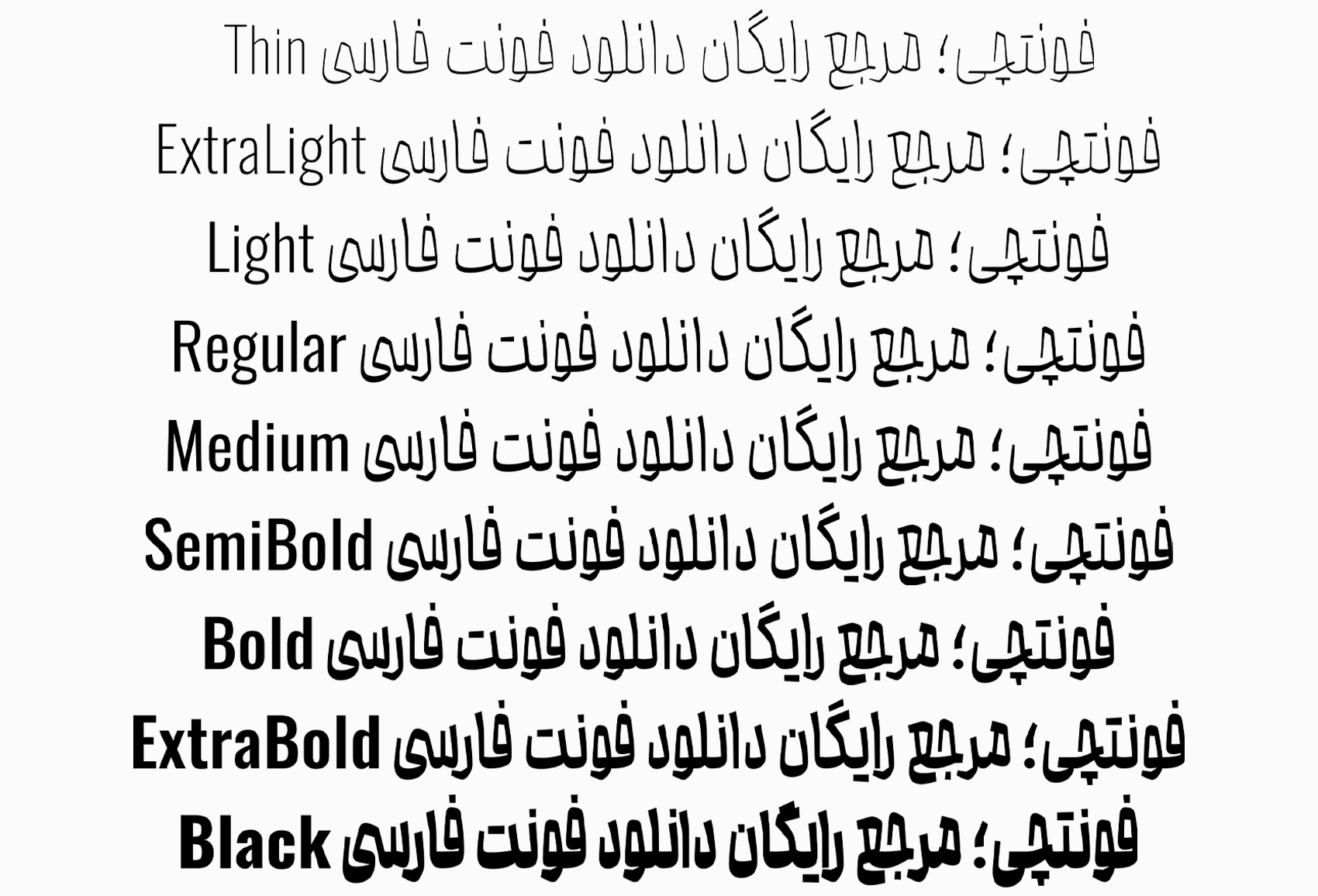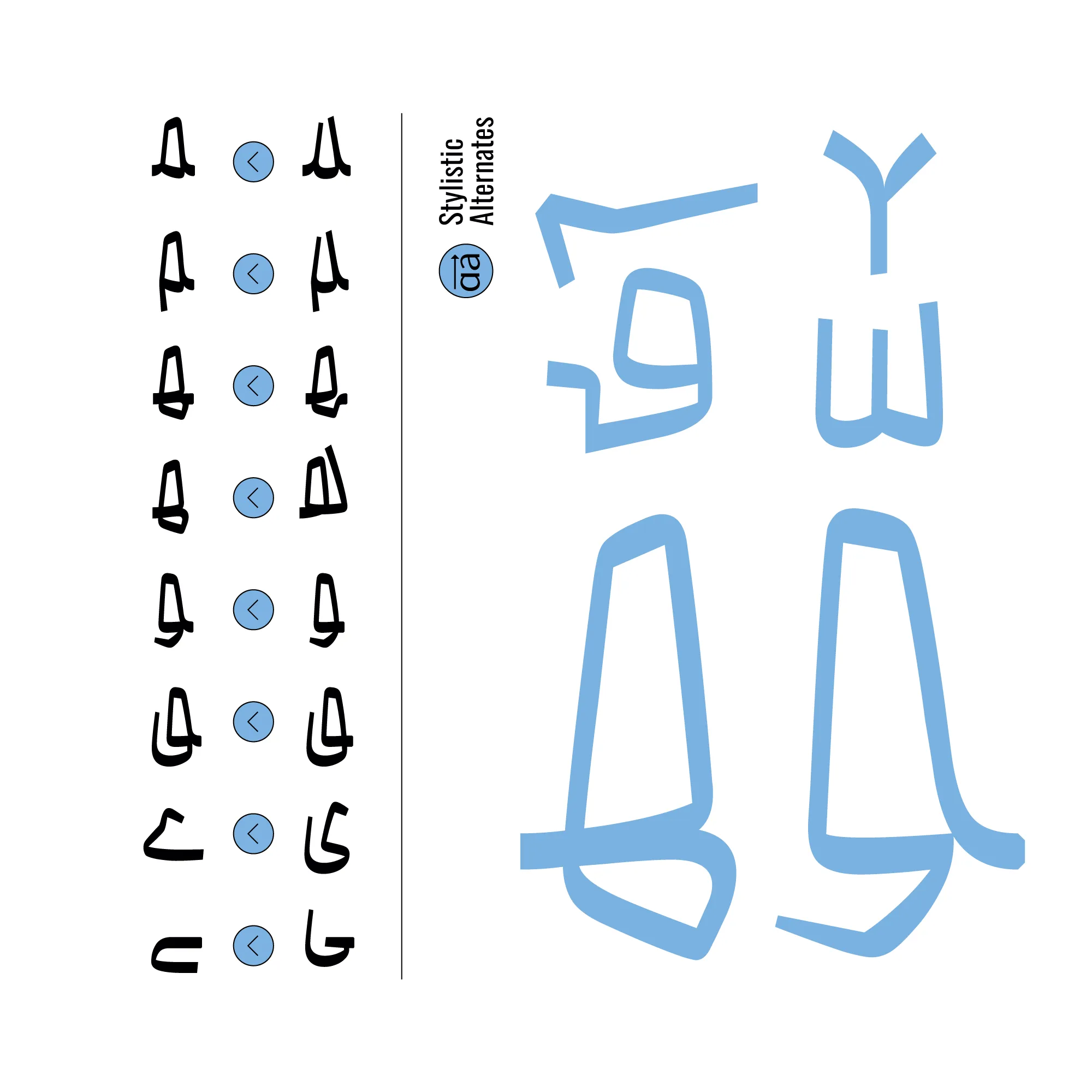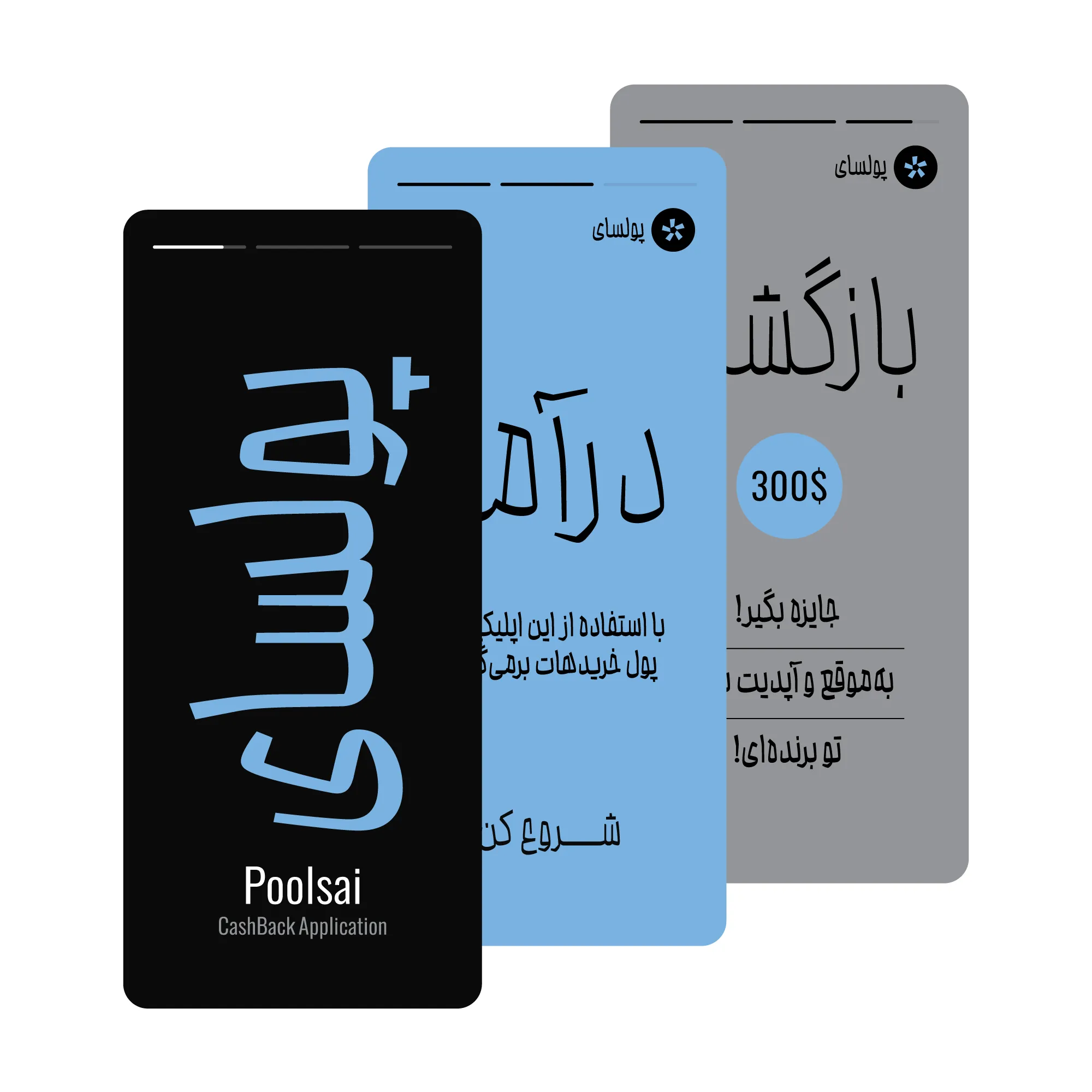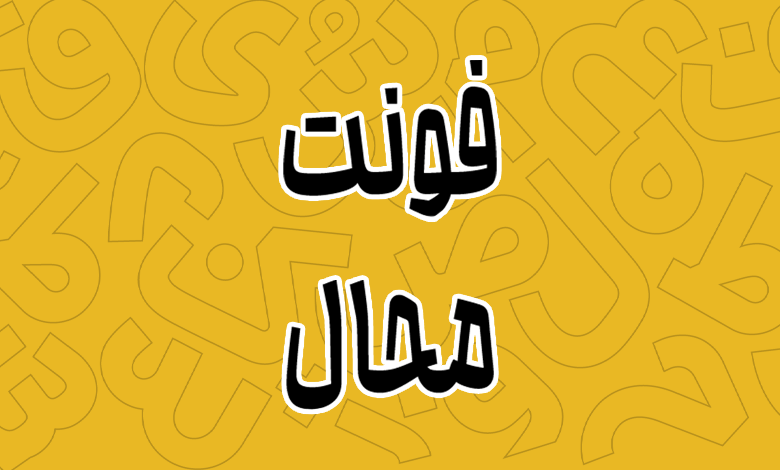
فونت محال (Mahal)
فونت محال (به انگلیسی: Mahal) قلمی با طراحی کاملا هندسی و ظاهری شبیه به خط نسخ است. این خط فارسی دارای ارتفاعی کشیده است و حروف از راستای افقی دارای ظاهری فشرده هستند که همین ویژگیها آن را به قلمی مدرن برای تبلیغات تبدیل کرده است. فونت محال رایگان نبوده و با توجه به پشتیبانی که از ۵ وزن مختلف و ویژگیهایی همچون نسخه مخصوص اعداد فارسی، حروف جایگزین و گلیفهای تزئینی و ریال را در خود دارد، در قالب ۳ بسته قابل دانلود است.
سید ناصر خادم که پیش از این قلمهایی مثل فونت ادامه و فونت مدام را طراحی کرده، این فونت جدید را بهمنظور قلمی برای تبلیغات، خصوصا در فضای دیجیتال و شبکههای اجتماعی معرفی کرده است. قلمی که با ظاهر پرانرژی و مدرن خود، دارای شخصیتی آرام و درونگرا است.
در ادامه این نوشته از سایت دانلود فونت فونتچی، به نقد و بررسی کامل فونت محال خواهیم پرداخت. خطی فارسی که میتوانید از آن بهترین استفاده را برای فضای تبلیغاتی و استفاده در عناوین به کار ببرید. فونتی که دارای ظاهری نمایشی ولی روحیهای نوجوان است.
فونت محال بهعنوان یک تایپفیس خلاقانه و نمایشی، با روحیهای معترض و جسورانه طراحی شده است. این فونت توانایی انتقال پیامهایی قوی و تاثیرگذار را دارد و مناسب افرادی است که به دنبال ایجاد تمایز و جلب توجه در طراحیهای خود هستند. در عین حال، فونت Mahal با حفظ انرژی و شور ذاتی خود، گاهی آرامش و عمق درونگرایی را نیز منتقل میکند.
سبک طراحی و وزن فونت محال
فونت فارسی محال با جزییات دقیق و فرمهای بازیگوشانه حروف، انتخابی ایدهآل برای تیترها، شعارها و متنهای کوتاه است. این ویژگیها آن را به گزینهای مناسب برای کاربردهای تبلیغاتی، طراحی تصاویر و تامنیل در شبکههای اجتماعی، استارتاپها، طراحان بازی، و پروژههای وب و اپلیکیشن تبدیل کرده است.
محال از ۹ وزن متنوع پشتیبانی میکند که از وزن بسیار نازک تا بسیار تیره را شامل میشود. در وزنهای سبک، ضخامت حروف شباهتی به تایپفیسهای مونولاین پیدا میکند، در حالی که در وزنهای سنگینتر، کنتراست بیشتری در ضخامت حروف دیده میشود که به طراحی عمق و جذابیت بصری بیشتری بخشیده و همچنین ظاهری نمایشیتر بهخود میگیرد.
یکی از مهمترین چالشهای طراحی فونت محال، ترکیب عمودی بودن فرم حروف با حفظ خوانایی و اصول رسمالخط فارسی بوده است. کنترل فضای بین حروف، هماهنگی خطوط عمودی، و تنظیم ارتفاع دندانهها و حلقههای باز و بسته، از جمله جزئیات پیچیدهای بودند که در این پروژه بهخوبی مدیریت شدهاند. نتیجهی این تلاش، خلق تایپفیسی است که با وجود جسارت در طراحی، همچنان وفاداری خود به ساختار زیبای خط فارسی را حفظ کرده است.
سید ناصر خادم؛ طراح فونت محال.
پشتیبانی از ۵ زبان متنوع
فونت محال علاوه بر زبان فارسی، از زبانهای عربی، کردی و اردو که براساس رسمخط فارسی هستند پشتیبانی میکند. این فونت با چینش مناسبی که برای تمامی گلیفهای فارسی دارد، امکان استفاده در سایر زبانهای خاورمیانهای را فراهم نموده است.
در سایر زبانها که برخی حروف مانند «ک، ی، ه، ؤ، ئ» در عربی یا «ﮧ، ﮩ، ے» در اردو ظاهری متفاوت با نسخه فارسی دارند گلیف استاندارد خود را پشتیبانی میکنند. همچنین برای این زبانها کلیه اعراب و کارکترهای تزئینی زبان کوردی که بهوفور بر روی حروف استفاده میشود نیز گلیف اختصاصی با همان سبک طراحی درنظر گرفته شده است.
فونت Mahal انگلیسی نیز در این قلم پیادهسازی شده تا بدون نیاز به استفاده از فونت دیگری با همین سبک طراحی بتوانید از حروف لاتین انگلیسی نیز استفاده کنید. با اینکه برای زبان انگلیسی از طراحی اختصاصی بهره نمیبرد، طراحی و ظاهر تمامی حروف انگلیسی از فونت Oswald تحت لایسنس OFL وام گرفته شده است.
پشتیبانی کامل و حرفه ای اعداد
بخش اعداد فونت محال یکی از ویژگیها حائز اهمیت این خط فارسی است. در این قلم اعداد برای تمامی زبانها به شکلی استاندارد پیادهسازی شده تا منطبق بر زبان انتخابی و صفحه کلیدی که استفاده میکنید، از اعداد استاندارد استفاده کنید.
در زبان عربی که اعداد «۴۵۶» دارای ظاهری متفاوت از اعداد فارسی «۴۵۶» هستند، گلیف اختصاصی برای این قلم در نظر گرفته شده است.
دارای حروف جایگزین حرفه ای
یکی از بهترین قابلیتهای فونت رایگان محال، پشتیبانی از حروف جایگزین (Stylistic Alternates) و ترکیبهای ویژه (Ligatures) است که امکان ایجاد جلوههای منحصربهفرد را فراهم میکند. این قابلیتها بهویژه برای تولید محتوا در شبکههای اجتماعی، طراحی پوسترها، و استوریها بسیار کاربردی هستند.
به کمک این حالت میتوانید با دانلود فونت محال برای فتوشاپ و فعال کردن ویژگیهای Stylistic Set برخی حروف را بدون نیاز به انجام کارهای پیچیده در نرمافزارهایی نظیر ایلاستریتور یا فتوشاپ با ظاهری متفاوت تایپ کنید که در تصویر بالا نمونهای از این حروف را مشاهده میکنید.